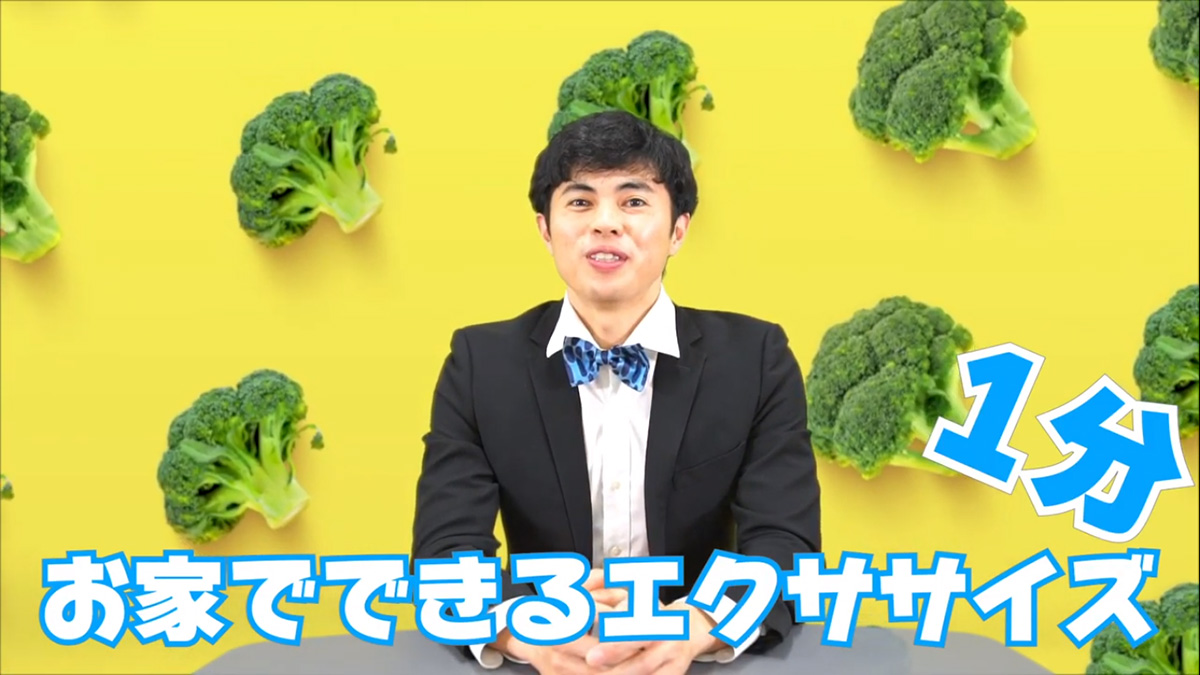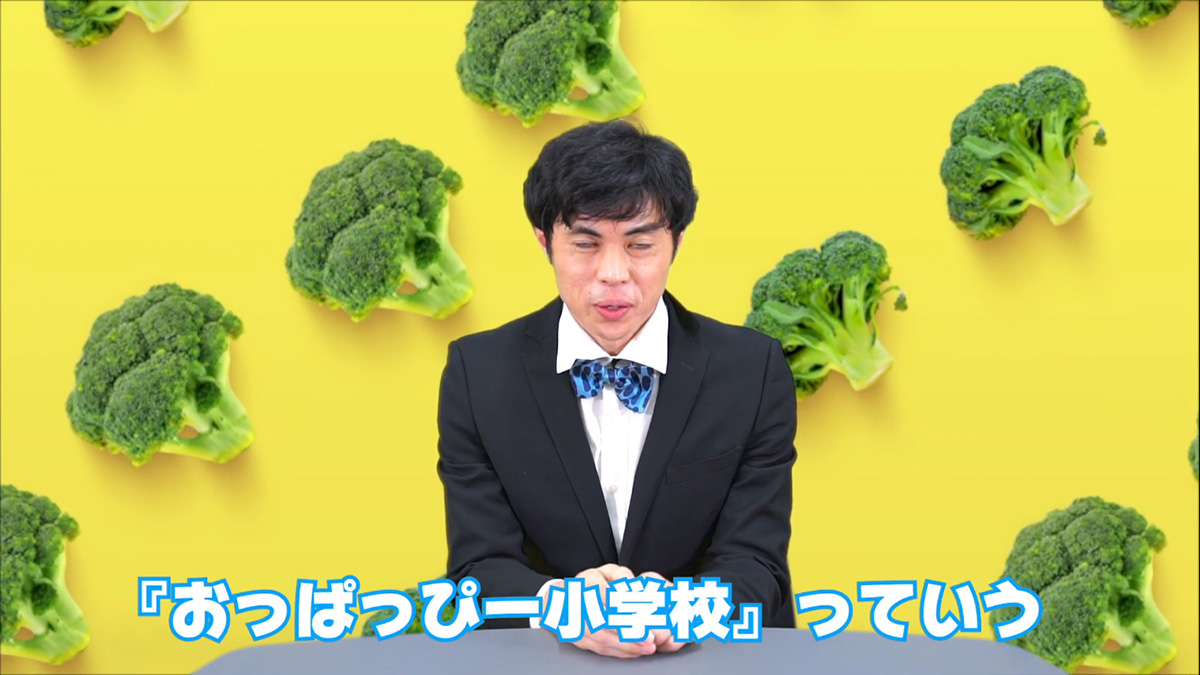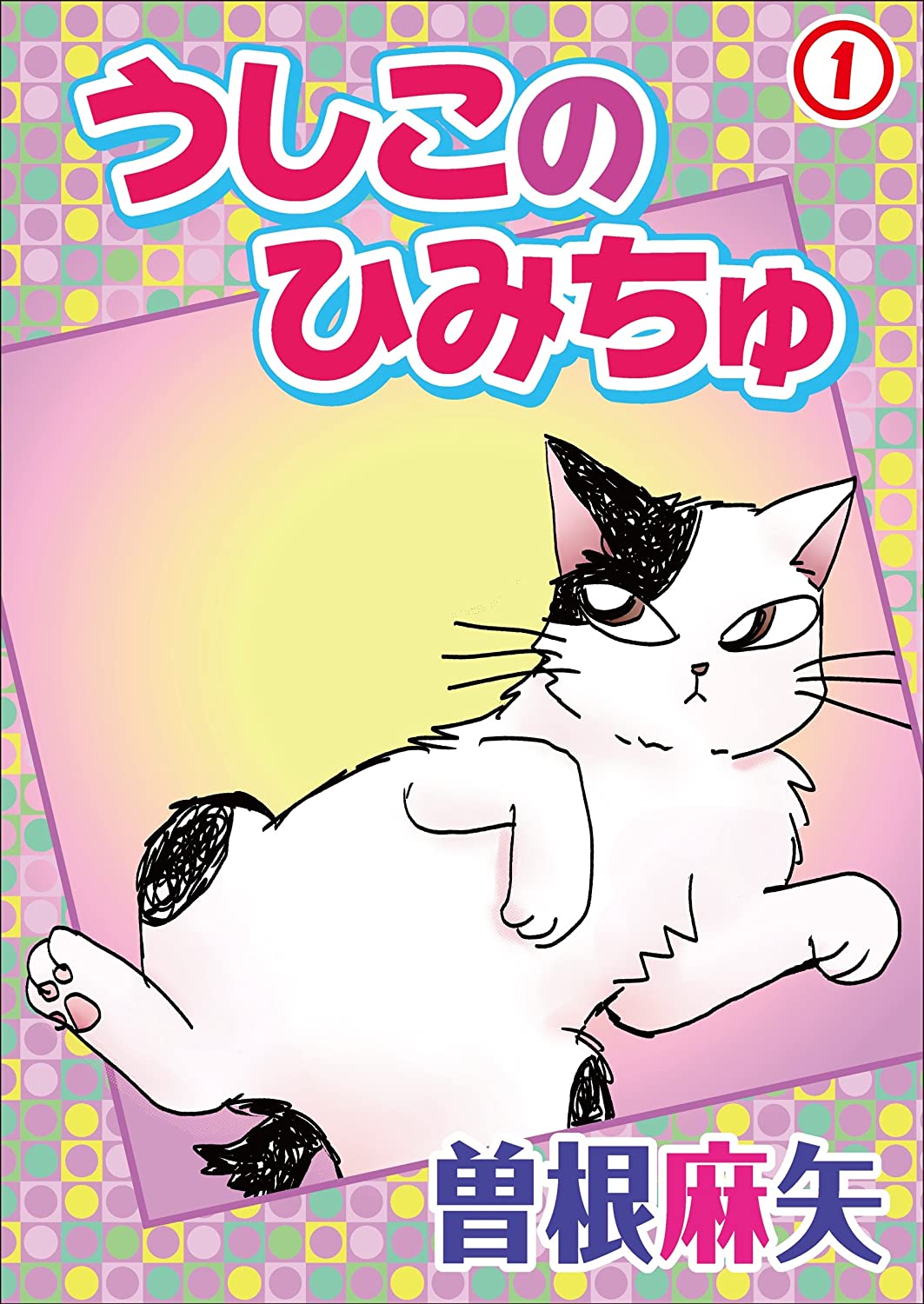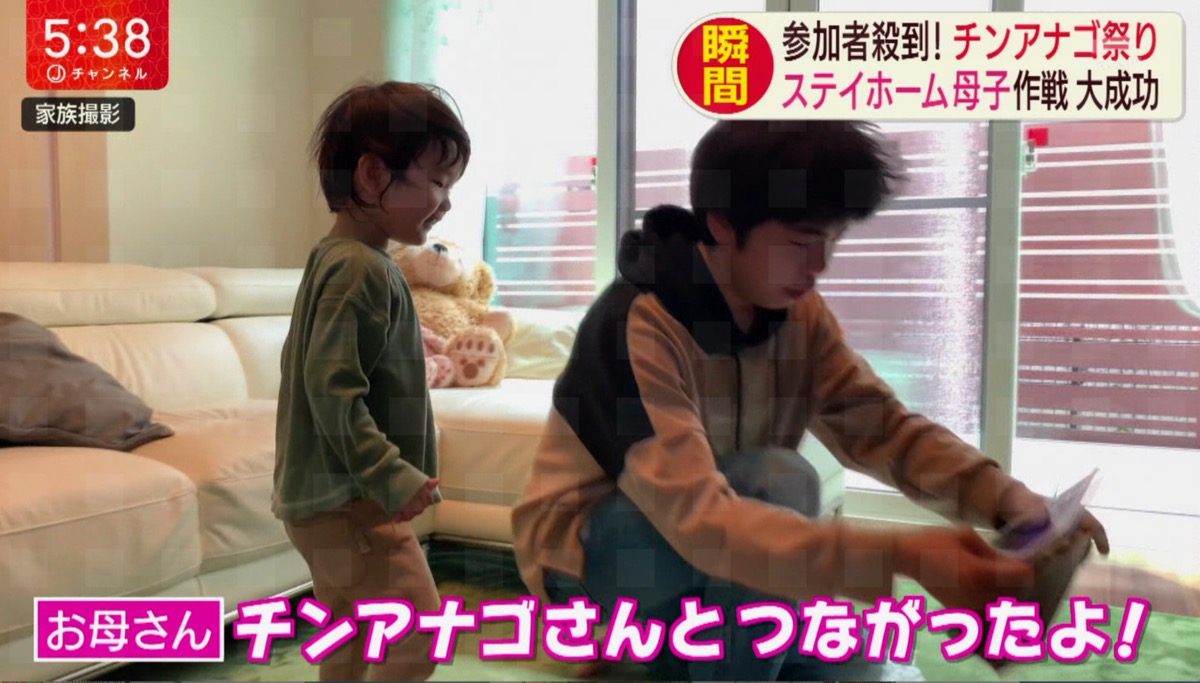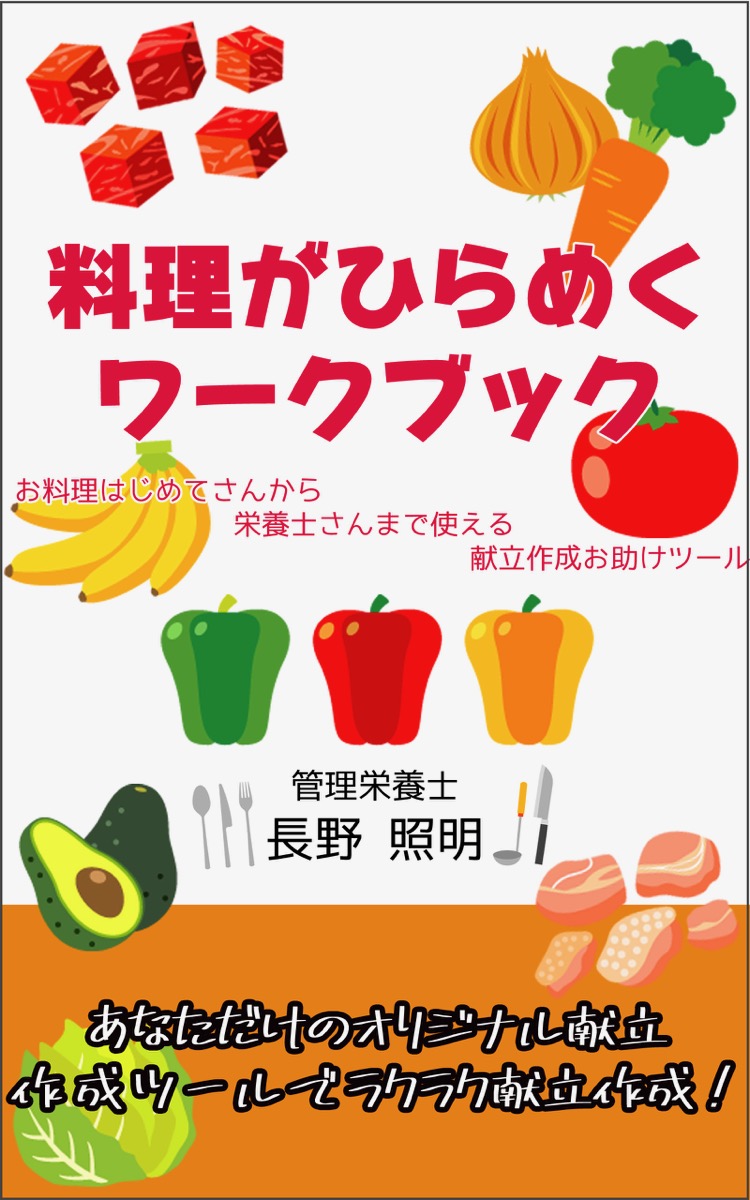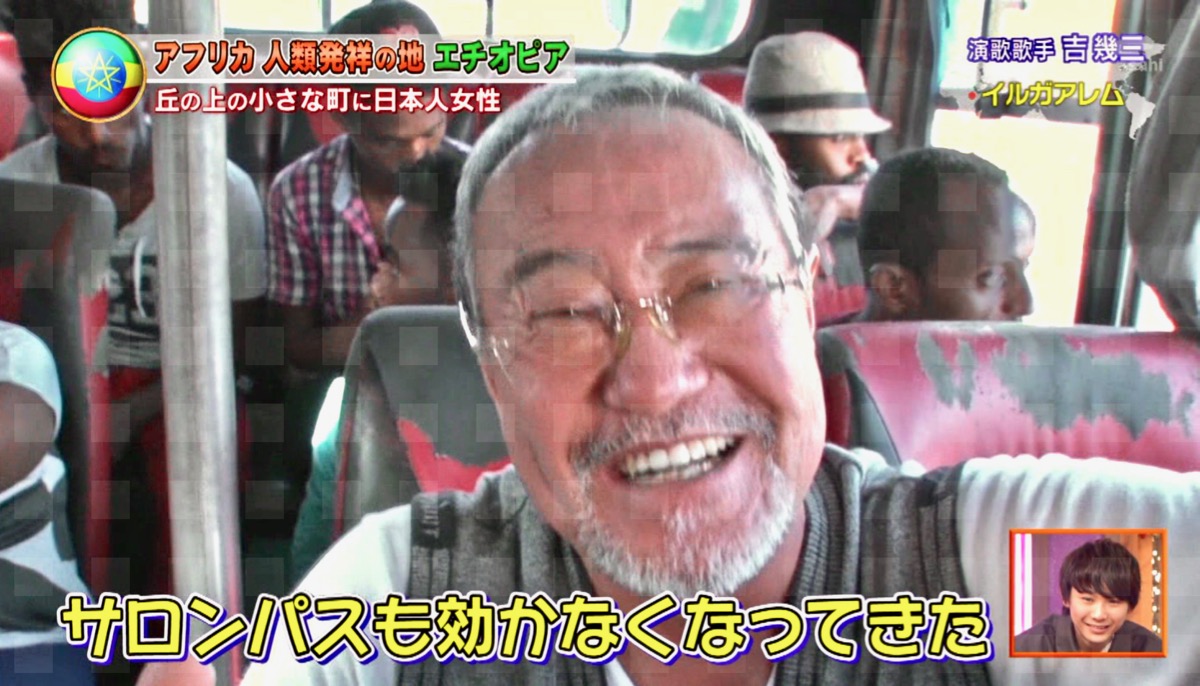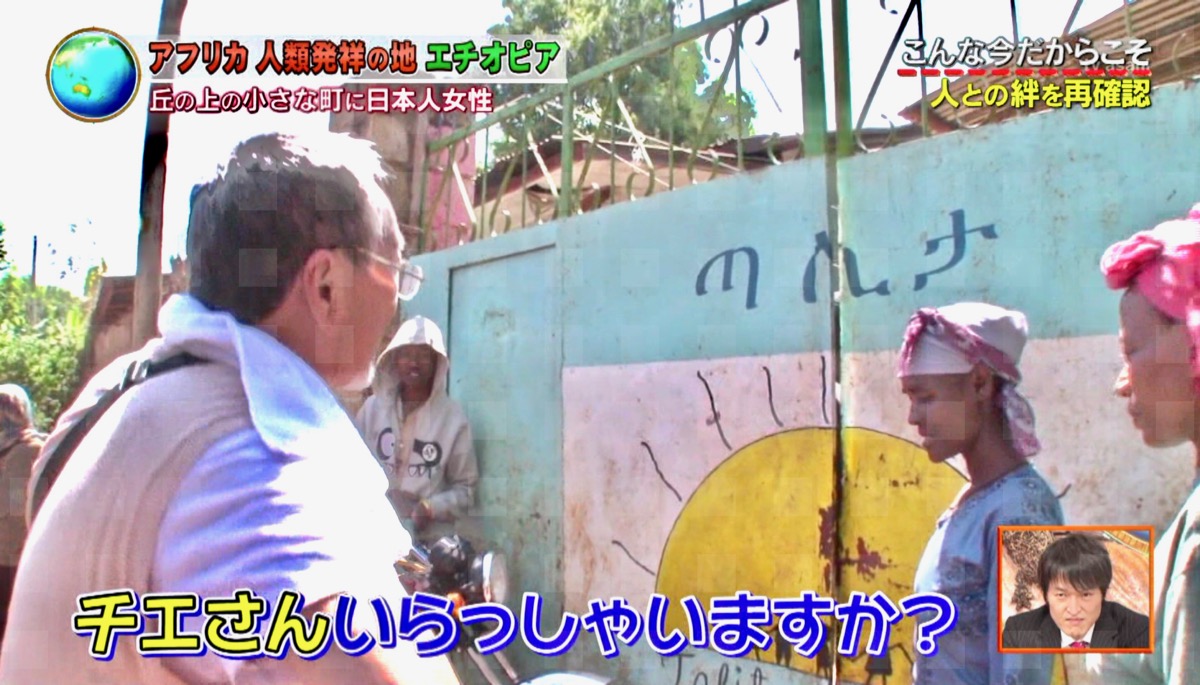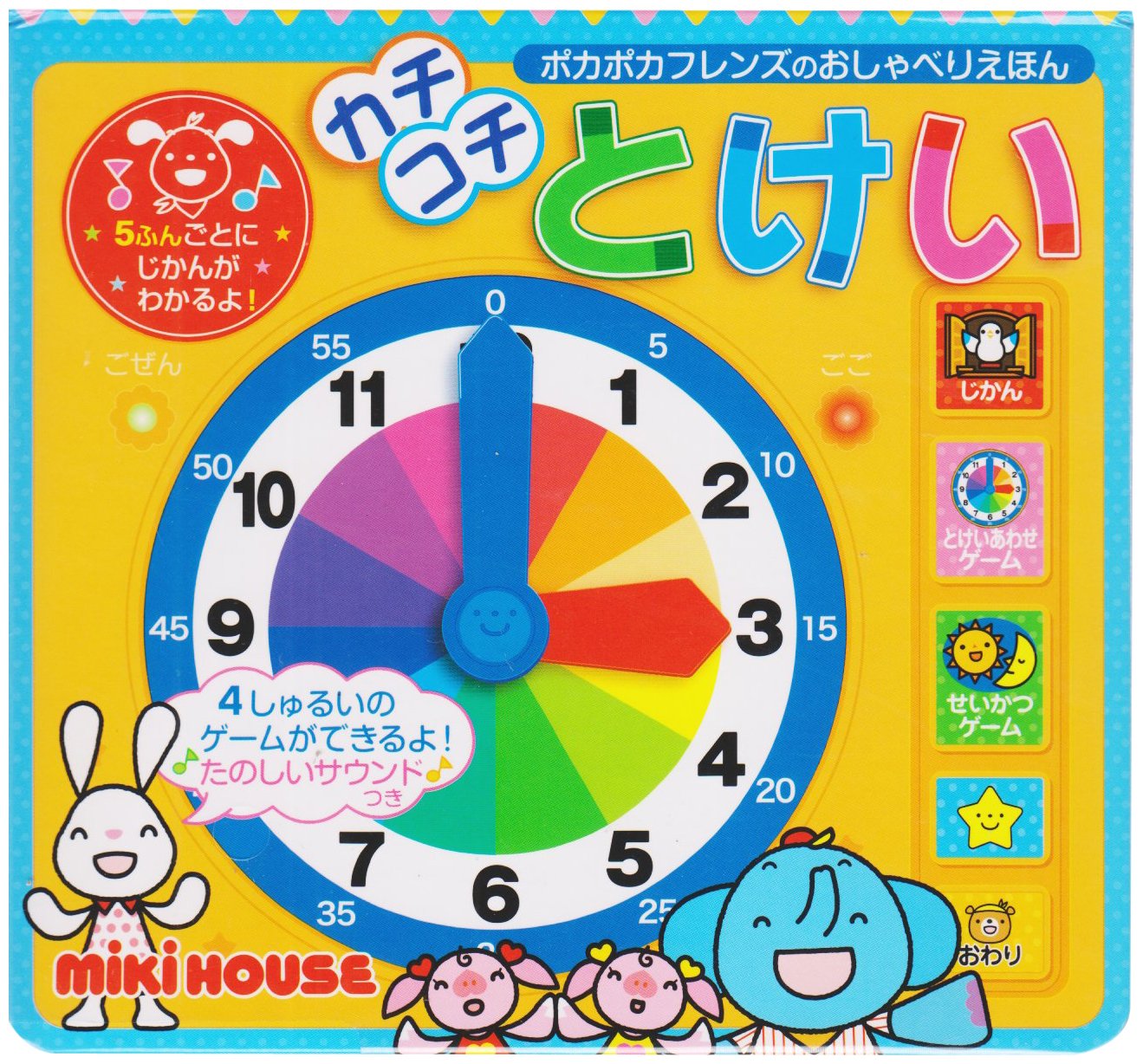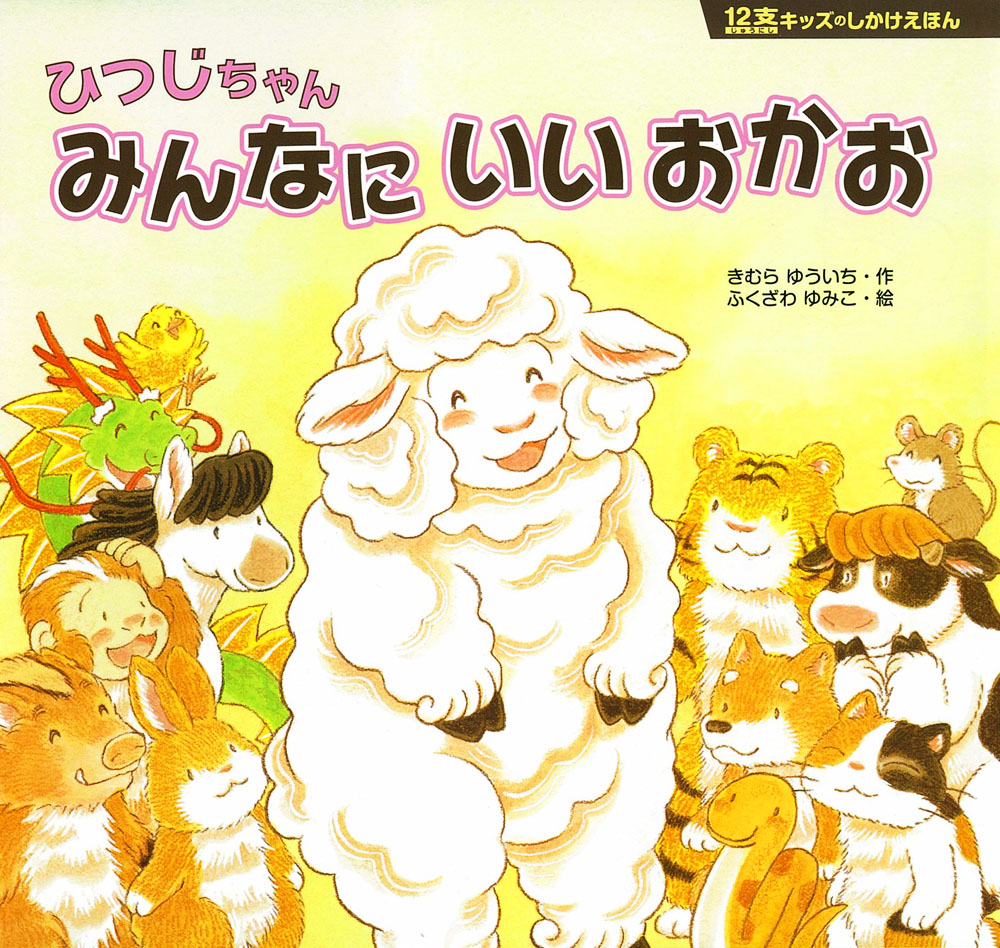
「クッキーラン:キングダム」というスマホで遊べるゲームの中で「ハッピールイカ」が使われています。
どうやら、組込みで使われているみたいです。
もう1枚。
こんな感じで好きな文字列を入力できます。
スマホゲームアプリ「クッキーラン」シリーズについては、
京成線の駅ホームに掲示されていた。
この「新京成で行く」シリーズのポスターでは毎年使われるようだ。
テレビ朝日「あいつ今何してる?」。
これも…。
書名:ぼくのかわいいおさるちゃん
著者:ウルフ・ニルソン、菱木晃子
発行:岩波書店
スシローのレポート動画に、
ハッピールイカが使われてました。
この画像でハッピールイカ確定。
もうひとつ。
動画編集専門チャンネル【エディステ】
【フォント】動画編集にオススメのフォント11選!
6分すぎからタイプラボのことが語られている。
22分50秒あたりからは、わんぱくルイカのことも…。
書名:まじめなオチンチンの話
著者:矢島暎夫
発行:カンゼン
書名:ぼくたちかめんライダー
原作:石ノ森 章太郎
文 :関口 美由紀
絵 :にあ・れい&ひろ・かねこ
発行:講談社
右下にはキャピー書体も使われている。
書名:わくわくあやとり
著者:福田けい
発行:bbc
日本テレビ「有吉ゼミ」。
もうひとつ…。